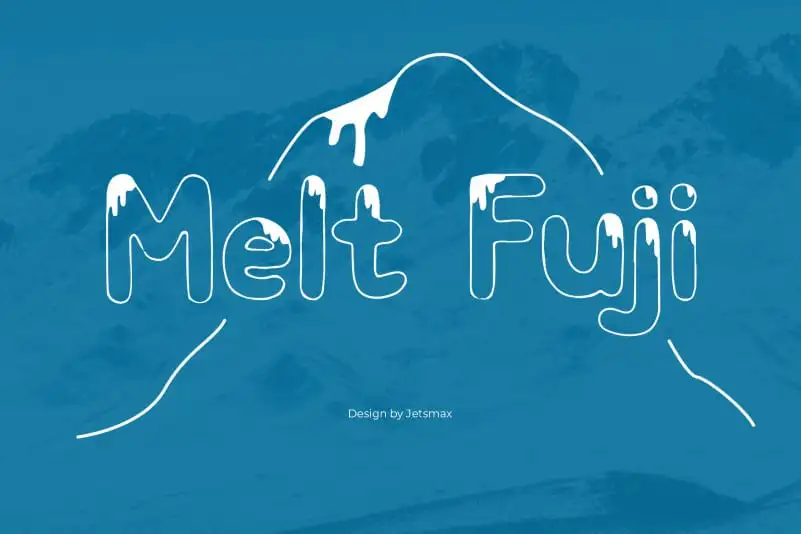
Melt Fuji Display Font – Download Grátis
A Melt Fuji Display Font é uma fonte de estilo display criada para designers que buscam agregar um toque único a suas criações. Inspirada no encantador e distinto cenário das montanhas cobertas de neve, esta fonte apresenta linhas leves e arredondadas que refletem a delicadeza da natureza invernal. Se você está em busca de um toque único para qualquer projeto visual, seja ele gráfico, design editorial ou sites, a Melt Fuji pode ser exatamente aquilo que lhe falta. Suas linhas fluidas e sua textura única tornam essa fonte uma escolha perfeita para dar um ar distintivo a qualquer projeto. Experimente ela em seus próximos projetos para ver como ela transforma seu trabalho de design.